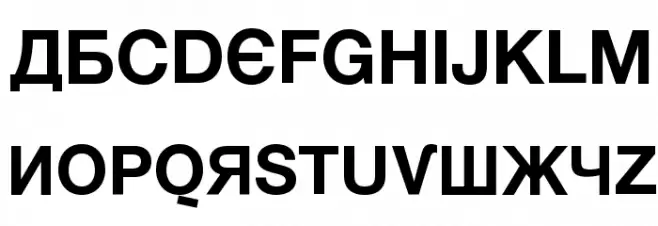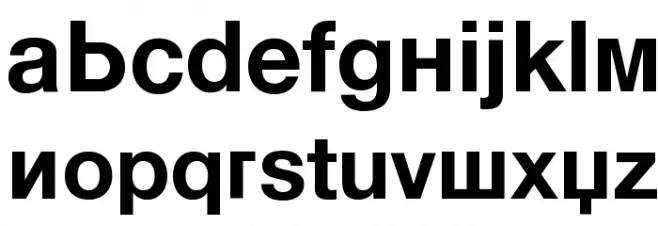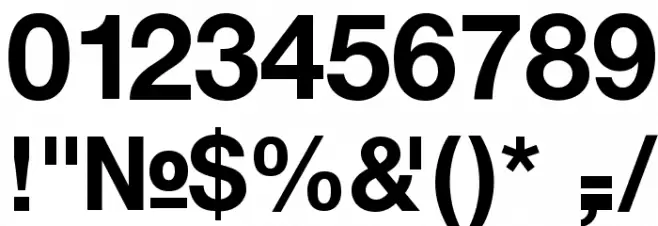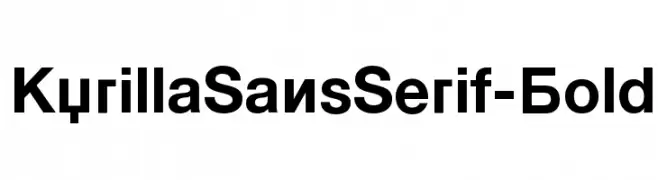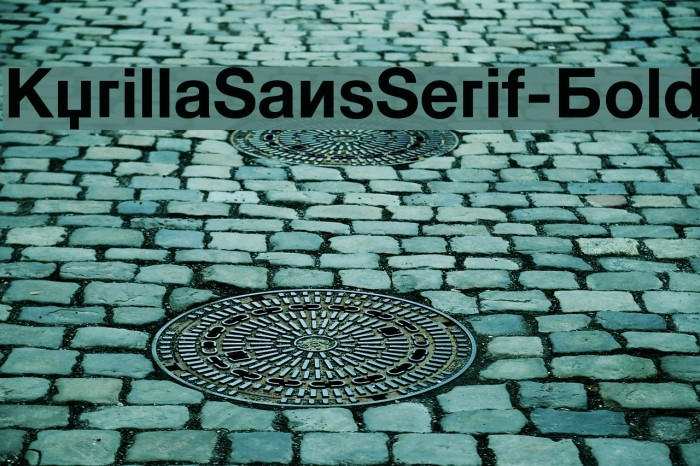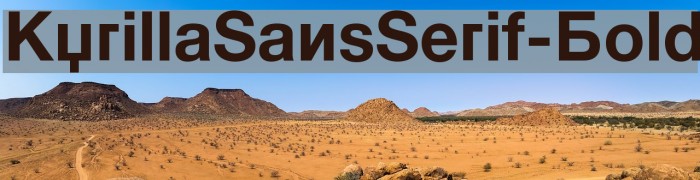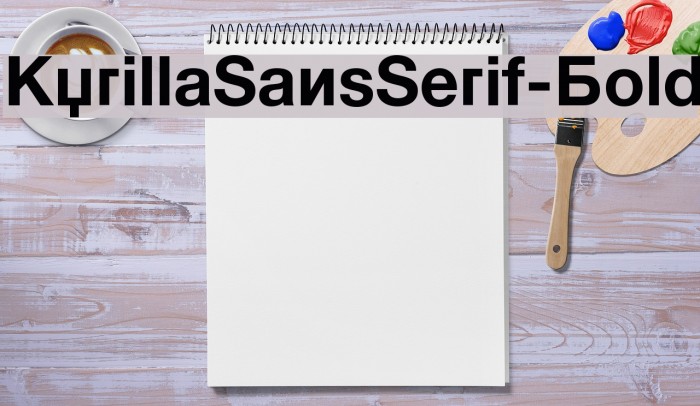
KyrillaSansSerif-Bold Font
Die erste PostScript-Schrift, die kyrillische & lateinische Schriftzeichen verbindet. Ein Joke-Font von MK, 25.3.92, vs.1.2000